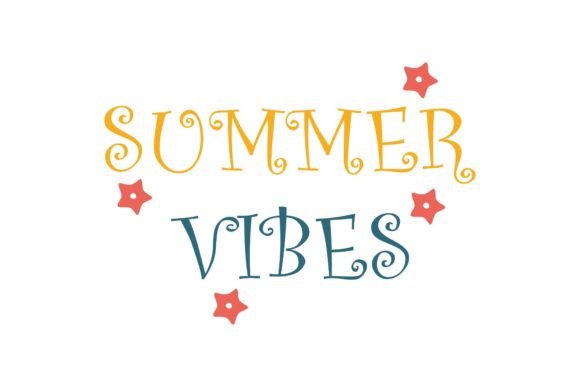
Quotes Summer Font
Att hitta rätt designelement kan vara utmanande, men Quotes Summer Font erbjuder en exceptionell samling som omedelbart lyfter ditt arbete.
Oavsett om du skapar POD-produkter (Print on Demand), bröllopsinbjudningar eller grafik för sociala medier, är Quotes Summer Font ett perfekt val.
Experttips: Kombinera dessa element med kompletterande typsnitt för att skapa unika, iögonfallende mönster som sticker ut.